想了解字型的設計方法卻又無從入手?
想買些入門版的字型設計書內容又太難明白?
思緒俠為你整理了五本簡單易明的字型之書,讓你在短時間內了解字型是什麼回事。
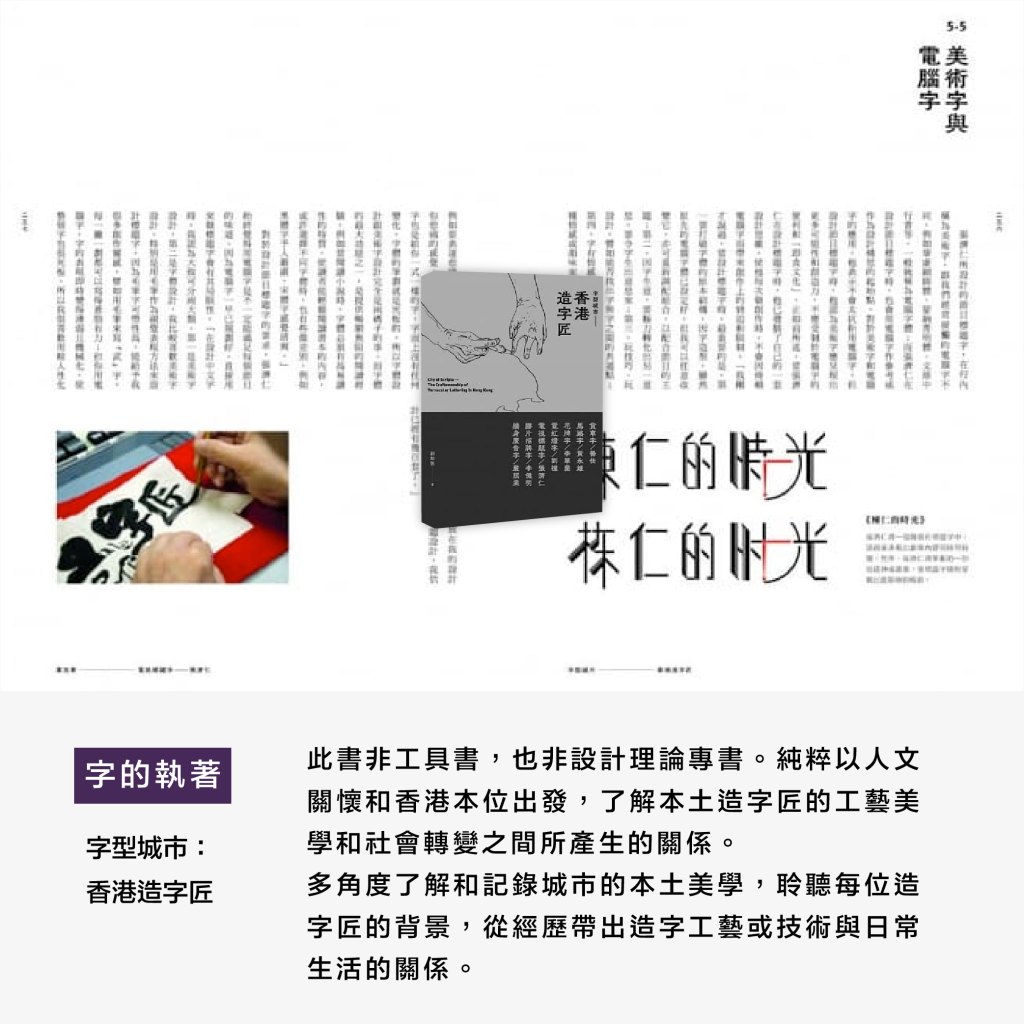
字的執著【字型城市:香港造字匠】
此書非工具書,也非設計理論專書。純粹以人文關懷和香港本位出發,了解本土造字匠的工藝美學和社會轉變之間所產生的關係。
多角度了解和記錄城市的本土美學,聆聽每位造字匠的背景,從經歷帶出造字工藝或技術與日常生活的關係。
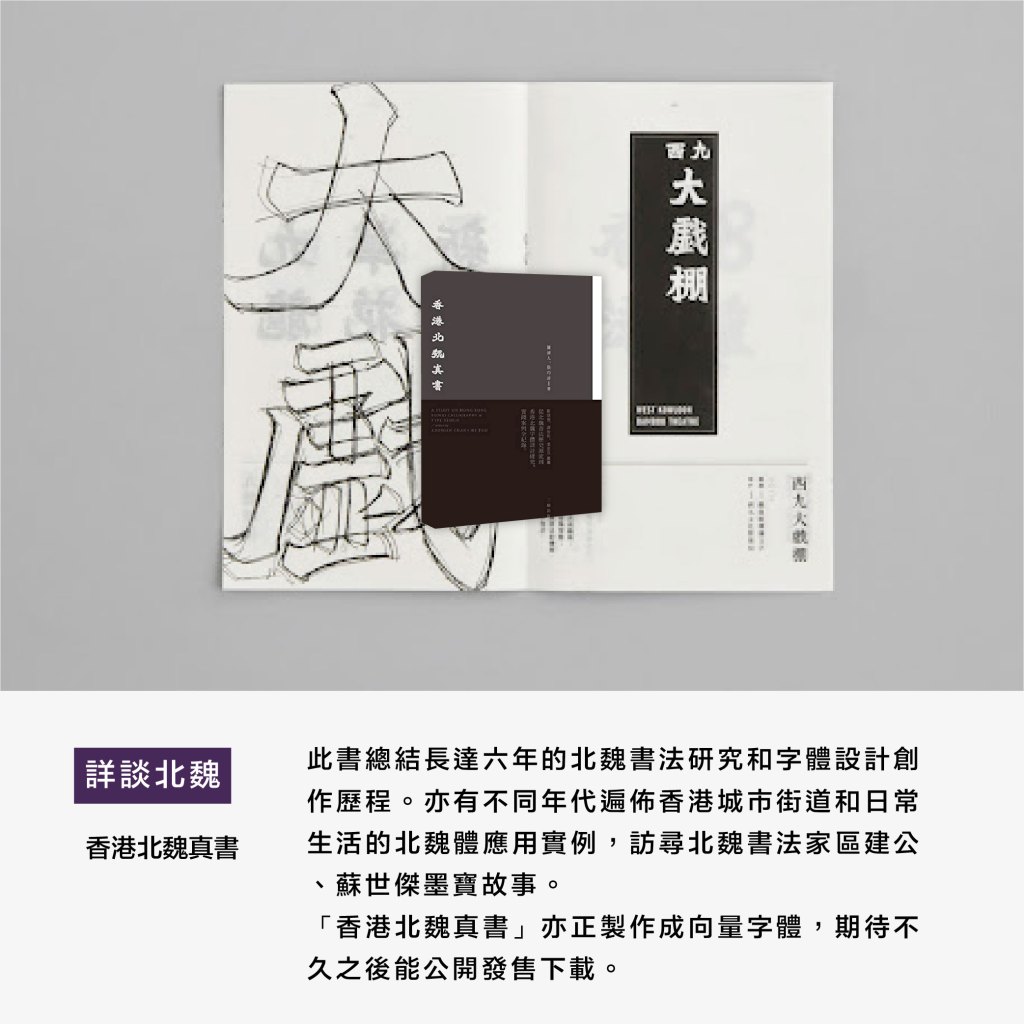
詳談北魏【香港北魏真書】
此書總結長達六年的北魏書法研究和字體設計創作歷程。亦有不同年代遍佈香港城市街道和日常生活的北魏體應用實例,訪尋北魏書法家區建公、蘇世傑墨寶故事。
「香港北魏真書」亦正製作成向量字體,期待不久之後能公開發售下載。
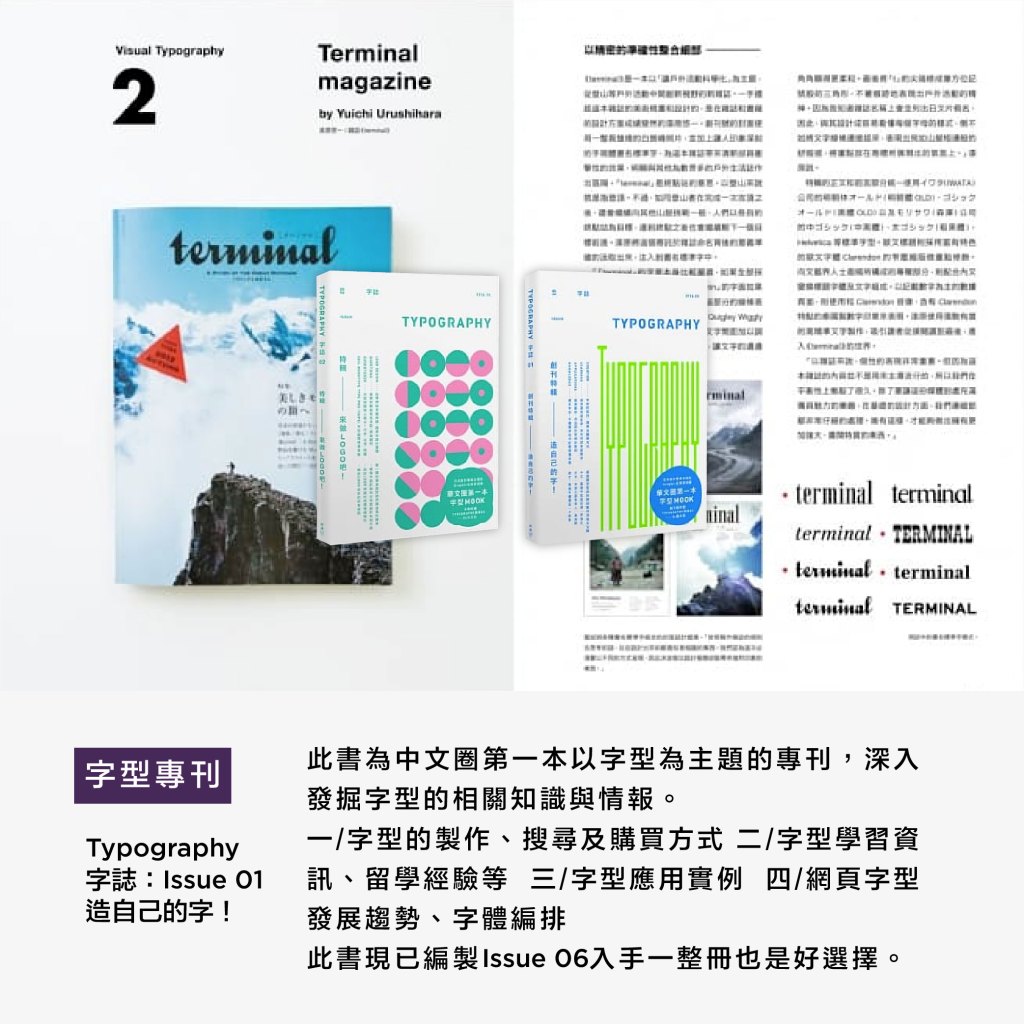
字型專刊【Typography 字誌:Issue 01 造自己的字!】
此書為中文圈第一本以字型為主題的專刊,深入發掘字型的相關知識與情報。
一/字型的製作、搜尋及購買方式 二/字型學習資訊、留學經驗等 三/字型應用實例 四/網頁字型發展趨勢、字體編排
此書現已編製Issue 06入手一整冊也是好選擇。
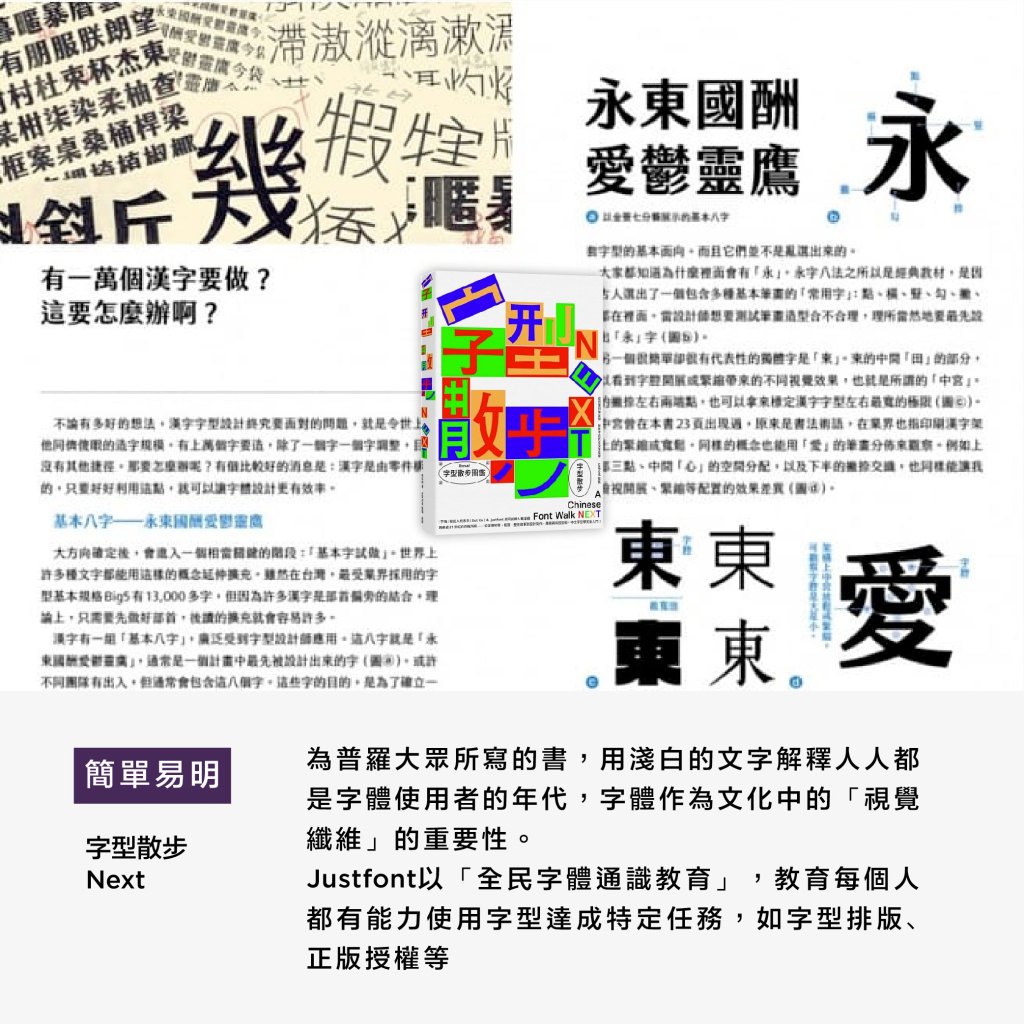
簡單易明【字型散步 Next】
為普羅大眾所寫的書,用淺白的文字解釋人人都是字體使用者的年代,字體作為文化中的「視覺纖維」的重要性。
Justfont以「全民字體通識教育」,教育每個人都有能力使用字型達成特定任務,如字型排版、正版授權等
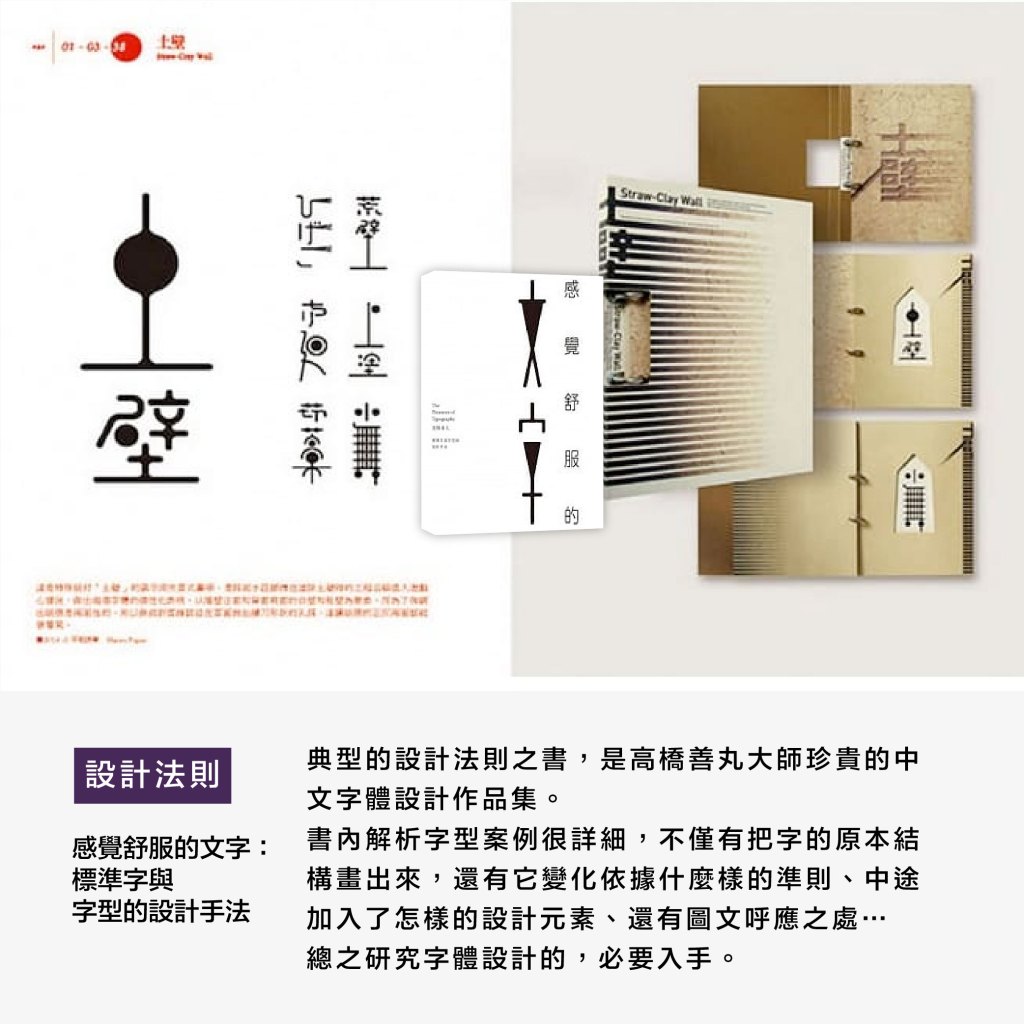
設計法則【感覺舒服的文字:標準字與字型的設計手法】
典型的設計法則之書,是高橋善丸大師珍貴的中文字體設計作品集。
書內解析字型案例很詳細,不僅有把字的原本結構畫出來,還有它變化依據什麼樣的準則、中途加入了怎樣的設計元素、還有圖文呼應之處…
總之研究字體設計的,必要入手。